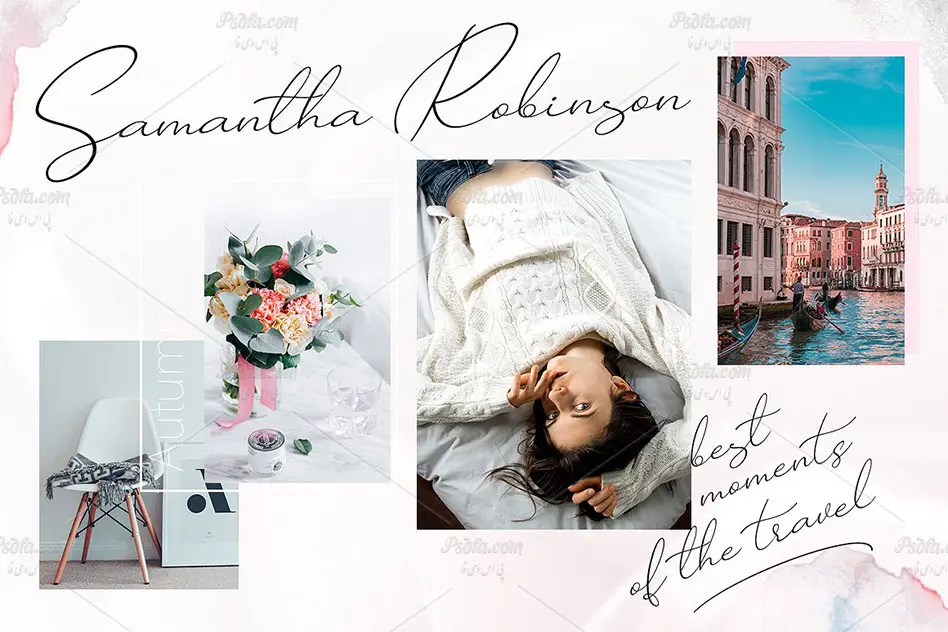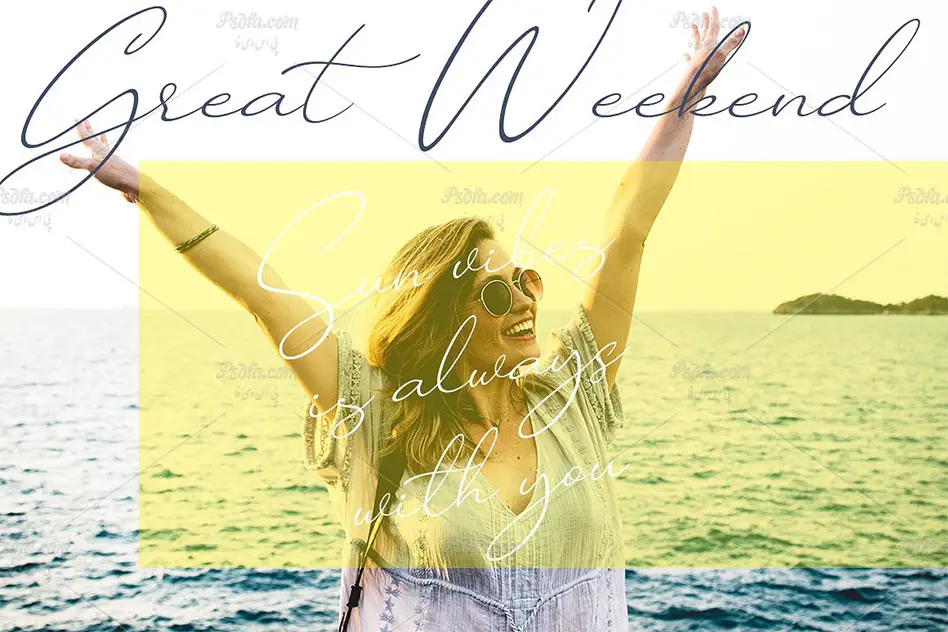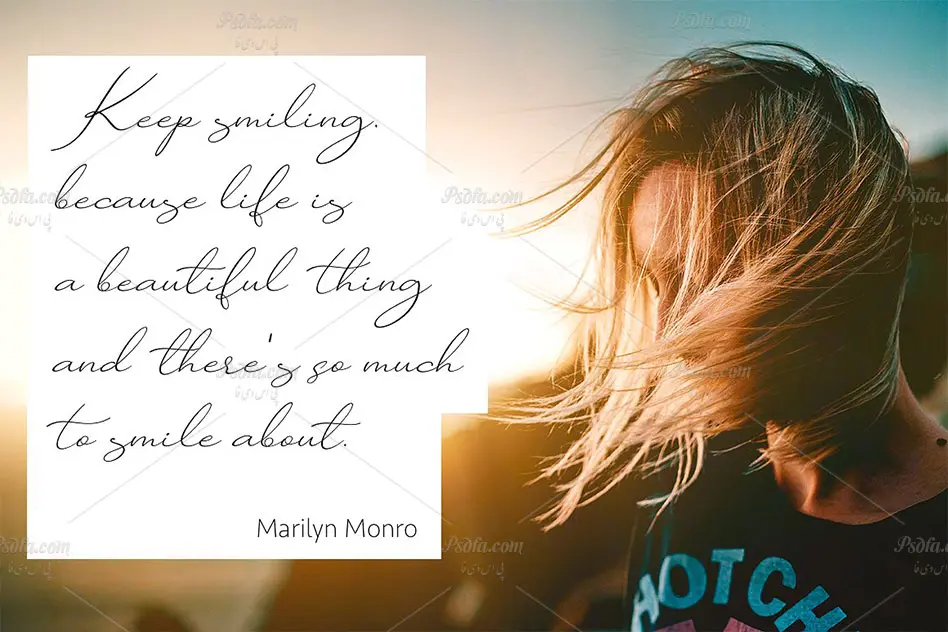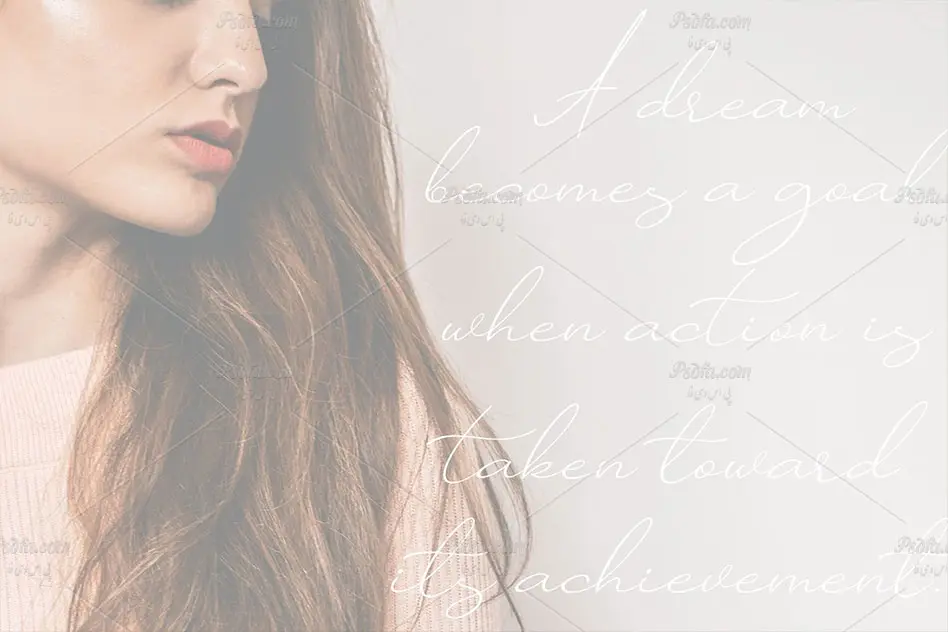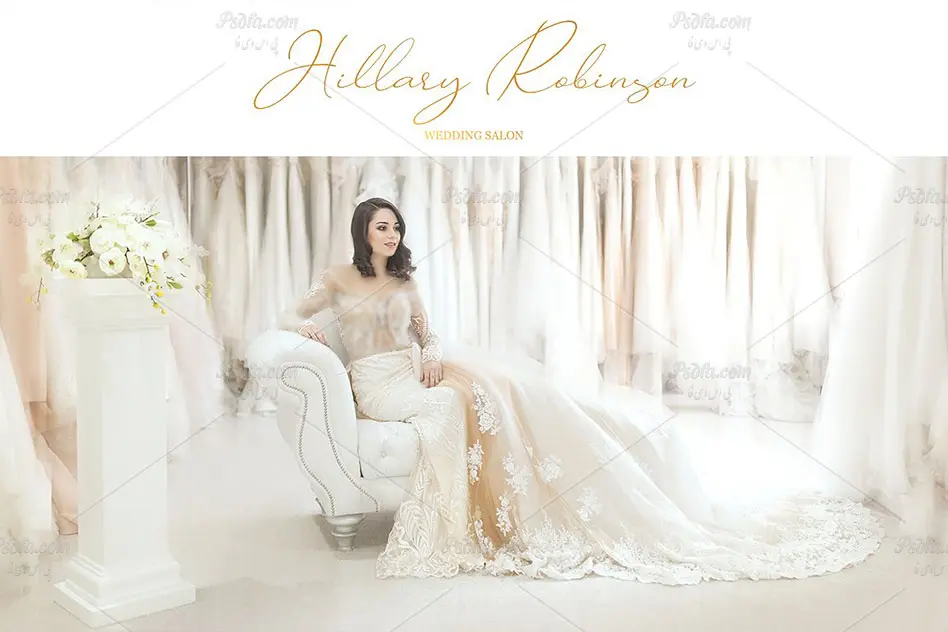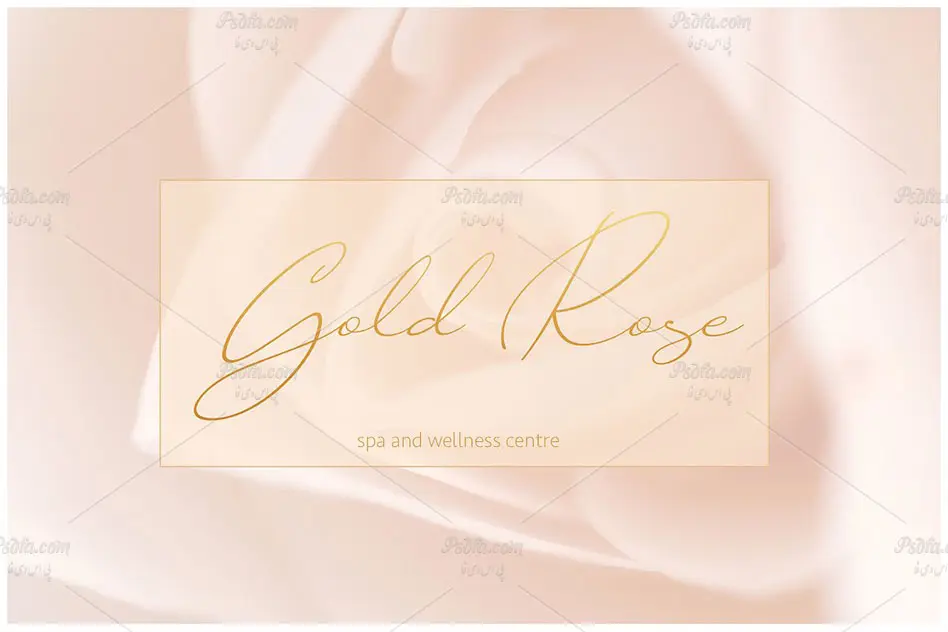
در این پست شاهد فونت انگلیسی بسیار زیبای Helardy طراحی شده به صورت دستنویس مناسب جهت استفاده در طراحی و گرافیک می باشید. این فونت زیبا در قالب فایل های eot , ttf , otf , woff و woff2 در سایت بارگذاری شده اند که با نصب یکی از دو فرمت otf یا ttf در پوشه فونت های سیستم قادر به استفاده از آن در تمام نرم افزارهای گرافیکی و ویرایشگر متن از جمله نرم افزار فتوشاپ ، مجموعه نرم افزار آفیس و … خواهید بود. فونت Helardy در وزن معمولی (Regular) طراحی شده است که از آن می توان در طرح های گرافیکی همچون طراحی انواع پوستر ، بنر ، تراکت ، بروشور ، کارت تبریک ، کارت پستال ، کارت عروسی و … استفاده نمود. همچنین از سایر فرمت های این فونت می توان در طراحی صفحات وب نیز استفاده کرد.
- نام فونت : Helardy
- وزن : معمولی (Regular)